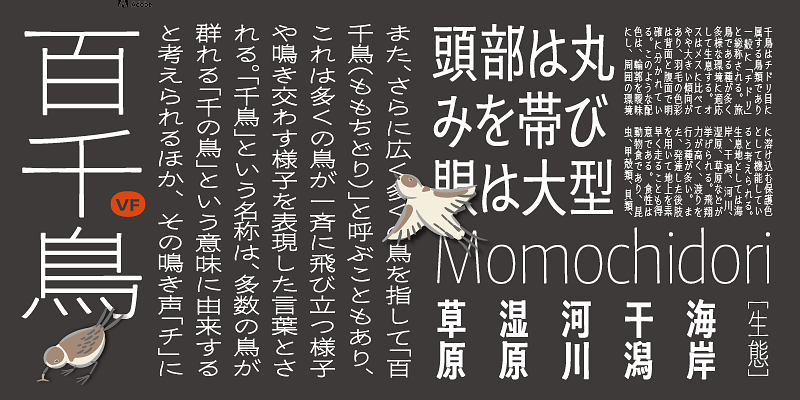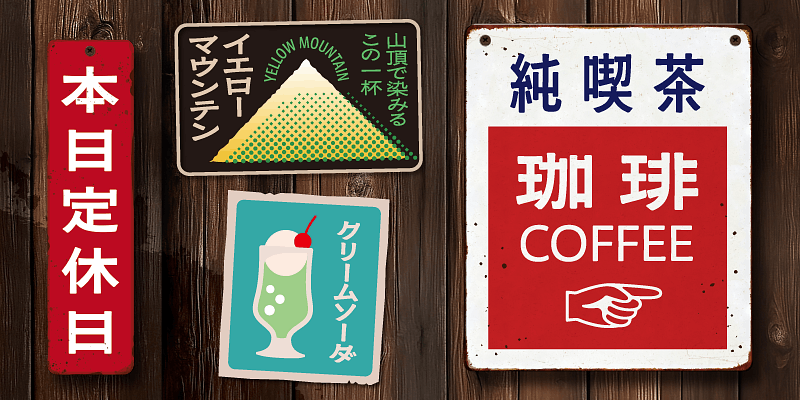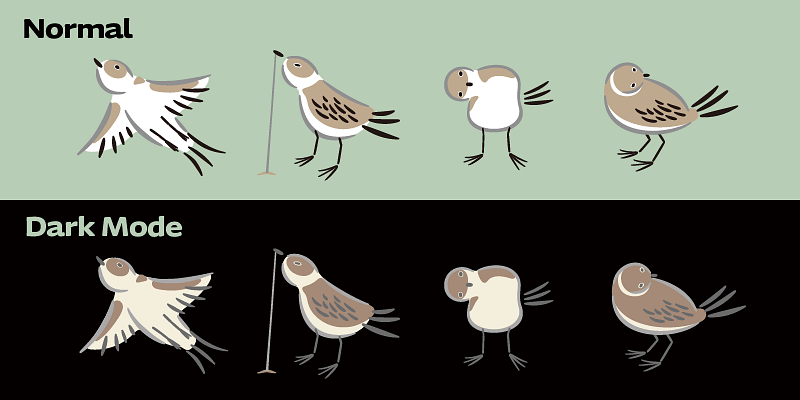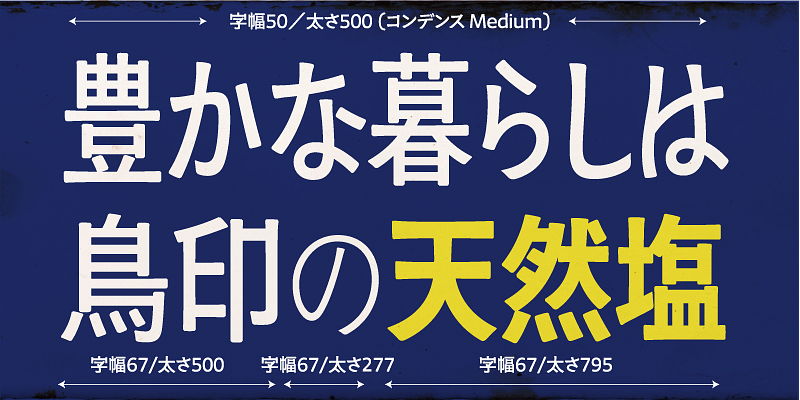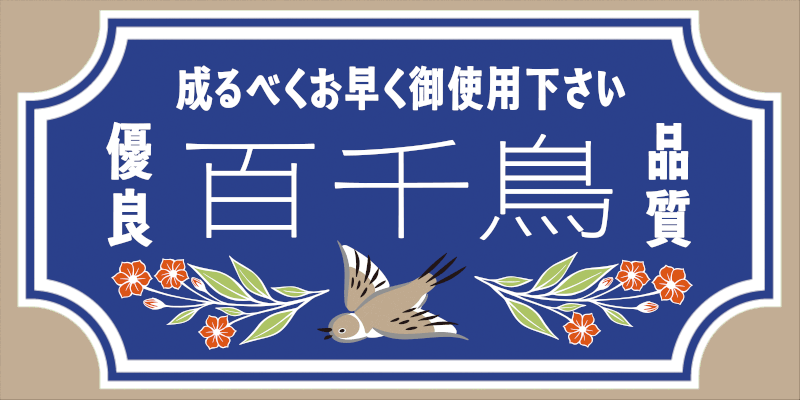
百千鳥(ももちどり)はユーモラスで懐古的なアドビオリジナル書体で、アドビのプリンシパル・デザイナーの西塚涼子によるデザインです。バリアブルフォントの技術によって、1つのフォントファイルだけを用いて、書体ファミリーに含まれる多様な太さやスタイルの連続するバリエーションの中のどれでも即座に選んで使うことが可能になりました。百千鳥では、太さのバリエーションだけでなく、縦長から横長までの広い範囲の縦横比の文字の形をカバーし、横組みにも縦組みにも対応する画期的な日本語バリアブルフォントです。
百千鳥VFの欧文イタリック軸はプロポーショナルの欧文だけに適用されます。